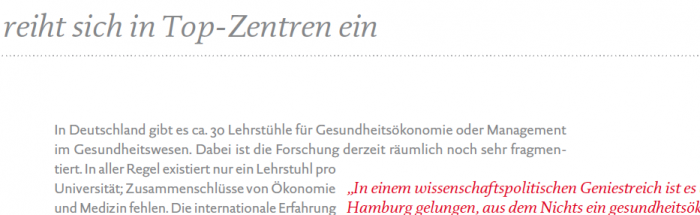
Alternative zu DTL Documenta Schriftart für Broschüre gesucht
meine Kundin ist auf der Suche nach einer Alternative zur DTL Documenta Schriftart für ihre Firmenbroschüre. Drei Schnitte der Dokumenta sollen knapp 500€ kosten, das liegt leider überhalb des Budgets.
Hat jemand einen heißen Tipp für mich, welche Typo der Documenta ähnlich kommt und etwas preisgünstiger ist?
Hier ein Screenshot:
Die FF Tundra gibt es nicht als Sans. Eine weitere Alternative wäre die FF Milo und die FF Milo Serif von Mike Abbink und Paul van der Laan. In allen Fällen sind die Kursivschnitte aber schmaler als die der DTL Documenta. Frank Blokland hat die Kursivschnitte der DTL Documenta etwas breiter gestaltet damit sie in kleinen Schriftgrößen und etwas längeren Texten gut lesbar ist.
Weil ich die Serifenlose sehe: FF Yoga von Dupré wäre evtl. noch eine alternative Sippe.
Des Weiteren könntest Du auch noch einen Blick auf die elegante Geneo von Elbaz werfen. Die macht auch in größeren Schriftgraden eine gute Figur. Passende Sans ist laut Typofonderie z.B. die Ardoise von Porchez. Da gehen auch andere, wie Deine Jetzige – nur dass Du einen Anreiz hast, falls Du noch etwas spielen möchtest. ;-)
ich wollte gerne noch mal Feedback geben, das es jetzt die Yoga geworden ist.